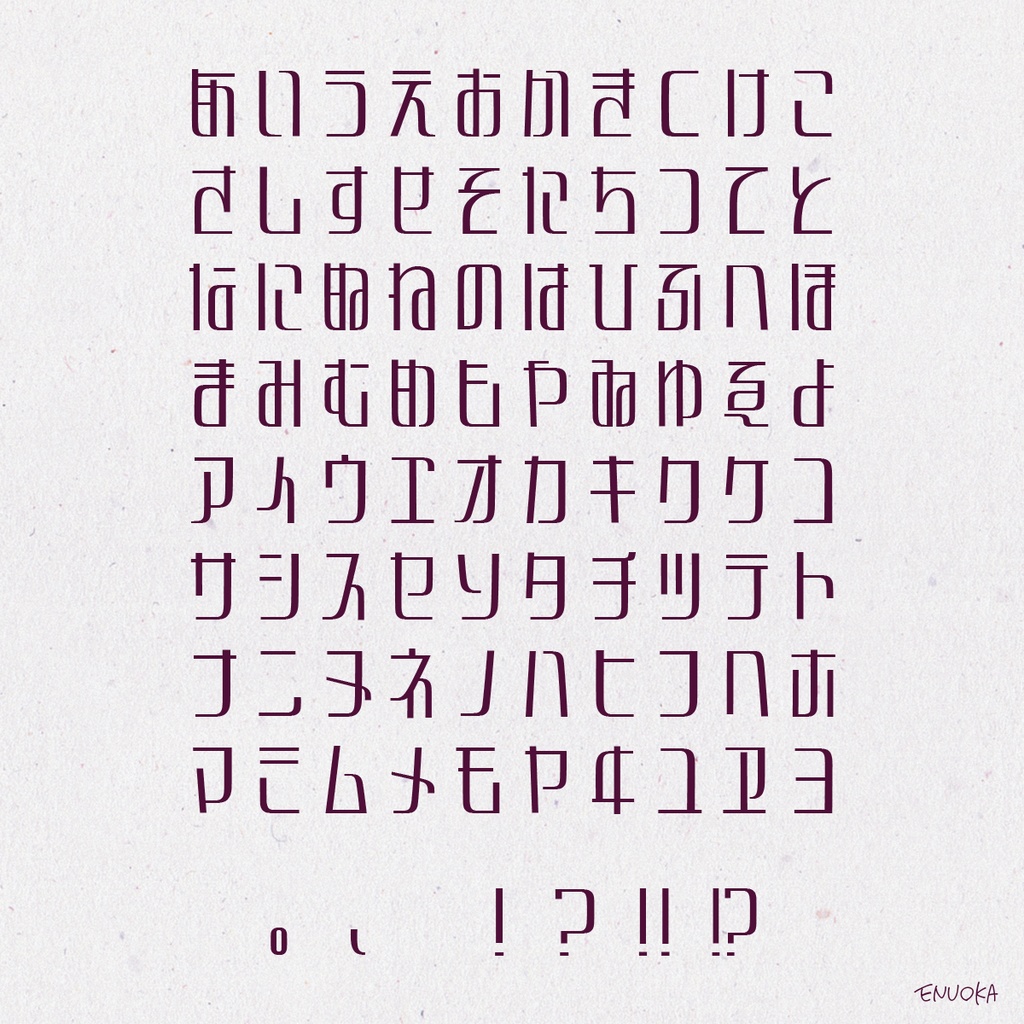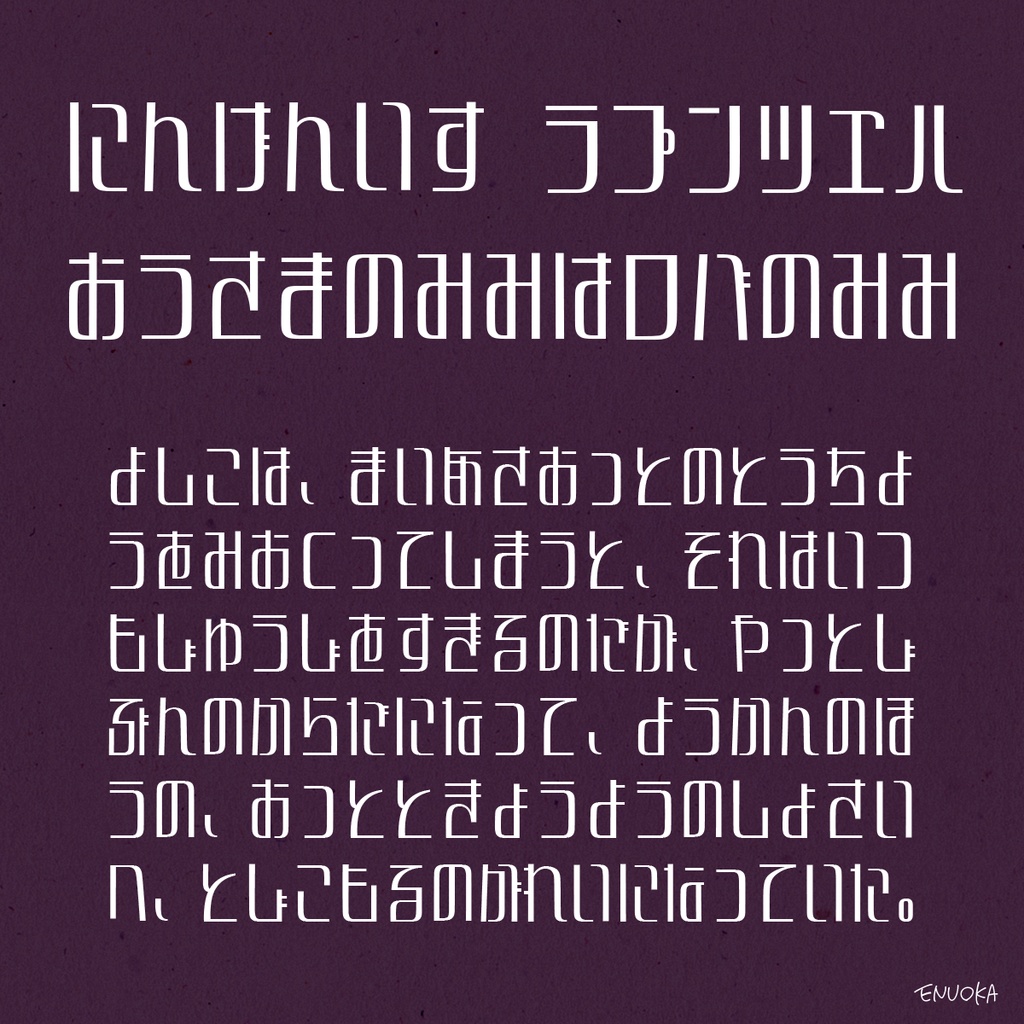
フリーフォント「わたしのために」
「わたしのために」は、強い執着心と孤独をモチーフにしたタイトル向けデザインフォントです。 短いタイトルやコピーに用いて、強いインパクトを出すのにおすすめです。 可読性が高くないため、長文にはあまり適していません。 ひらがな、カタカナのみの収録となりますのでご注意ください(英字は未収録です)。 【収録文字】 ・全角ひらがな、カタカナ ・ごく一部の全角記号類 !促音拗音や記号は縦書きにも対応しています。 【利用規約】 ・商用・非商用を問わず利用可能です。同人への利用も自由におこなってください。 ・作者は著作権を放棄していません。自作発言はご遠慮ください。 ・当フォントを利用して発生した、いかなる損害についても作者は責任を負いません。 ・フォントデータをダウンロードした時点で利用規約に同意したものとみなします。 【webフォント化、アプリや書籍などへのフォントデータの収録について】 ・サイトへ使用するためのwebフォント化やアプリへの埋め込み、書籍などへのフォントデータの収録を希望される方は、作者までご連絡ください。 ・また同時に、出典の記載をお願いしております。サイト内のどこか(フォントを使用しているページ以外も可)にダウンロードページへのリンク(https://enuoka.booth.pm/items/1398444)をご記載ください。 ・画像化しての使用、フォントデータの配布を伴わない書籍などでの使用については連絡不要です。 【禁止事項】 ・フォントデータの改変・無断転載・再配布・販売 ・当フォントを利用した制作物、ロゴなどの商標登録 【注意事項】 ・ダウンロードデータ内には利用規約、.otfデータ、.ttfデータが収録されています。 ・予告なしにバージョンアップを行うことがあります。 ・一部の端末、ソフトウェアでは使用できない場合がございます。 21.12.05 サンプル画像を1枚差し替えました。 22.02.09 利用規約に「webフォント化、アプリや書籍などへのフォントデータの収録について」の項目を追加しました。